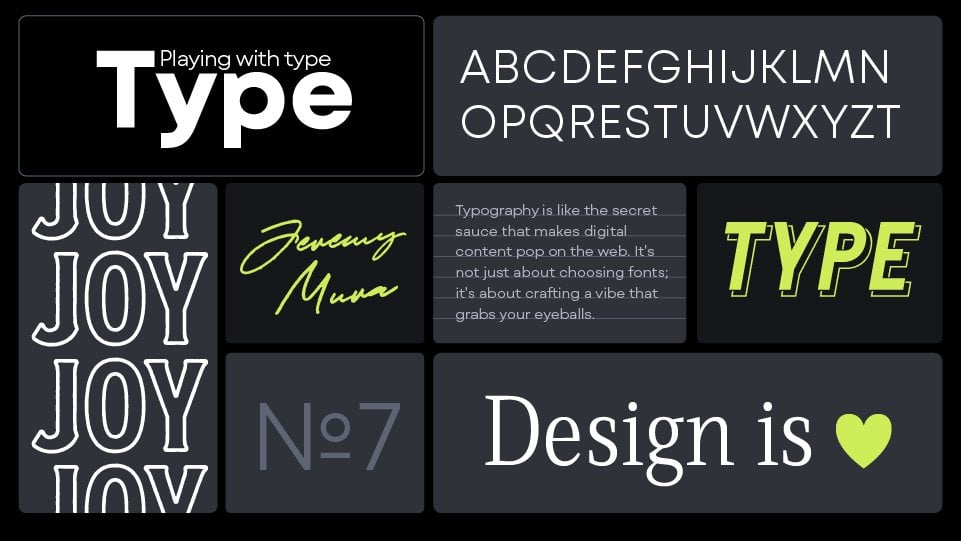
Jouer et concevoir avec la typographie pour les marques
Introduction
Inspiration et trouver des polices
Choisir les polices
Jumelage de polices
Personnaliser des polices et des logotypes
Systèmes typographiques
La puissance des glyphes
Composition et mise en page
Mon système logiciel de polices
Les besoins en typographie
9:24
Un excellent design typographique sépare les designers amateurs des pros.
Apprendre à manier des polices et les utiliser pour obtenir les bons résultats dans n'importe quel projet de conception créative.
Nous explorerons l'interaction dynamique entre type et branding, en apprenant mes méthodes de choix des polices, de personnalisation et de utilisation dans un site Web, une marque ou un design numérique.
Apprenez ceci :
✨ Maîtriser la typographie dans Branding : sélectionner et manipuler des polices qui correspondent aux identités de la marque, créer des visuels qui communiquent efficacement.
✨ Choisir et jumelage des polices : mon processus de sélection des bonnes polices pour un projet
✨ Glyphes et systèmes de polices : appliquer les principes de design et comment utiliser la typographie de manière créative
✨ Personnaliser les logotypes Développer des compétences en création de compositions typographiques visuellement époustouflantes à l'aide d'outils et de méthodes de conception numérique avancés.
✨ Exemples de clients : je vais montrer comment j'ai personnalisé des polices pour de vrais clients.
✨ Codes de triche de Jeremy : apprendre mes codes de triche pour travailler plus rapidement.
1. Introduction: Bonjour, bienvenue dans ce court cours sur la façon de jouer avec la typographie dans le domaine de l'image de marque et du design. Je m'appelle Jeremy. Je suis un designer de marque originaire de Sydney, en Australie, et je crée depuis dix ans maintenant. Et j'ai travaillé avec des clients de différentes marques. Et je crois que la topographie est à la base d'un design de qualité. Dans ce cours, vous apprendrez notamment comment utiliser la typographie dans un système d'identité Je vais donc vous montrer quelques exemples concrets de clients illustrant la façon dont j'ai sélectionné certaines polices et comment je les ai présentées pour créer une identité de marque. Je partagerai également avec vous mes conseils et réflexions sur la façon dont j'associe les polices pour différents projets. Ce qu'il faut sélectionner, comment s'y prendre, vous savez, utiliser les bonnes polices dans les bonnes situations. Je vais également expliquer comment personnaliser et choisir la bonne police et comment la manipuler dans Adobe Illustrator. Je vais également vous parler du pouvoir des glyphes et de la façon de personnaliser certaines polices et lettres lorsque vous travaillez sur la conception d'un logo Et comment faire en sorte que cela se démarque et devienne plus emblématique. Je vous montrerai également mes codes de triche, mes astuces, mes raccourcis et tous ces petits avantages en cours de route pour vous aider en tant que designer à grandir et à améliorer votre maîtrise de la Je vais également vous donner quelques devoirs et activités vous permettant de pratiquer la conception dans la section projet, afin que vous puissiez le faire pour pratiquer la conception et télécharger votre projet. Et je serais heureuse de vous faire mes commentaires afin que vous puissiez améliorer vos compétences. Alors, cliquez et lancez dès aujourd'hui et améliorez votre conception grâce à la typographie 2. Inspiration et trouver des polices: Au cours de l'année, j'ai probablement accumulé plus de 10 000 fonds. Et c'est parce que je télécharge toujours de nouvelles polices. Et chaque projet a besoin de quelque chose de différent. Et il y a toujours de nouvelles limites qui apparaissent, où il y a tout un tas de fonds gratuits très haute qualité Je veux vous montrer quelques sites qui vous inspireront, où vous pourrez télécharger des polices gratuites et acheter des fonds. Mais si vous voulez plus de ressources, je mettrai un lien dans la section du projet pour partager ma méga liste de ressources de conception. La première étape serait le partage de polices. Maintenant, ils ont 100 polices gratuites et gratuites. J'adore utiliser le partage de polices car il est puissant et propose de nombreux styles différents, quelques polices de script. Mais je l'adore parce que vous pouvez vraiment regarder différentes paires. En haut, vous avez des paires sur lesquelles je peux cliquer, cela me montrera en fait des paires différentes. La police est géniale. Un autre est le tissu de police. J'ai également utilisé leurs polices de caractères. Ceux-ci sont de très haute qualité. Ils ont des tas de styles différents. Par exemple, si je clique sur Mont, vous pouvez voir qu'il devient fin très clair jusqu' à devenir épais et noir. sites en italique comme celui-ci sont vraiment bons Pangram, Pangram propose des kits de démarrage 29$ où vous pouvez vous procurer tout un tas de polices à essayer, puis si vous en aimez certaines, vous pouvez les Ces polices sont vraiment cool, certaines sont futuristes, donc il y a plein de trucs sympas ici Vous avez également de futures polices, Xyz, elles sont vraiment géniales Il y en a une grande variété ici. Ce ne sont pas seulement des polices simples, mais aussi des polices d'affichage, rétro funky et intéressantes. Vérifie ça. Vous pouvez également vous rendre sur Creative Market. Create Market fournit également des polices de caractères. Si vous cliquez sur la section des polices, ils ont des lettres noires vintage, des graffitis cursifs fantaisistes Ils ont des tas de polices différentes. Vous pouvez également taper dans la barre. Tu peux voir à quoi ça ressemble. C'est également un excellent moyen de trouver des polices très rapidement. est un autre site sympa Nick.com est un autre site sympa. Brandon possède un studio de design typographique Il crée de nombreuses polices de caractères ici. Et il propose également ces packs, qui sont vraiment sympas, où vous pouvez trouver environ 2030 polices dedans J'adore son style. Il y a vraiment quelque chose de différent là-dedans. Si jamais vous travaillez sur des trucs rétro vintage, ceux-ci seraient parfaits pour ce type de projet. Il existe de nombreuses autres polices, comme les polices et les polices futures, etc., mais j'ai tendance à éviter les sites de polices gratuites très populaires car ils sont de très mauvaise qualité, en particulier en ce qui concerne les polices de caractères. Lorsque vous téléchargez une police, elle est défectueuse, il n'y a qu'une seule police, il n'y a pas plusieurs polices. Il ne s'agit donc pas d'une police de caractères de toute une famille de polices C'est pourquoi j'essaie d'éviter ces sites et je vais essayer de m'en tenir à ceux où j'en achète ou en télécharge un site gratuit sur un site comme Font Share, qui est tellement meilleur parce que la qualité est au rendez-vous. Vous pouvez voir qu'il a été méticuleusement conçu et fabriqué. Et il est également livré avec des glyphes et des symboles, ainsi que des variations sur différentes lettres C'est pourquoi je préfère cela, et j' essaie d'éviter des choses comme une police de caractères. Et si je tombe sur un site Web ? L'un des outils que j'aime utiliser s'appelle en fait font Ninja. Vous pouvez également utiliser quelque chose comme quelle police. Il s'agit d'une extension Chrome gratuite. Ce que je peux faire, c'est aller sur un site Web et peut-être que j'aime cette police ici. Tout ce que j'ai à faire c'est de cliquer sur la police Inga. Nous allons essentiellement scanner le site Web et me dire quelle police ils utilisent. À l'heure actuelle, je peux le voir avec Satoshi. Maintenant, Satoshi est une police gratuite sur le partage de polices. C'est la police de caractères qui s'y trouve. Ensuite, je peux placer ma souris sur la police et elle m' indiquera le poids, le fil et la couleur. Nous pouvons voir que tous ces petits détails dans cette petite boîte, vous pouvez voir ceux-ci comme 20 pixels, 15 pixels en utilisant une couleur grise. C'est vraiment cool. J'adore ça. Vous pouvez également jouer avec ces petits réglages ici. Vous pouvez déplacer la police, l' agrandir pour pouvoir la prévisualiser et jouer dessus. J'aime bien ça. Vous pouvez également ajouter les polices à vos favoris. Si vous cliquez sur le signet dans la police Inger, c'est ce qu'il fera. Voici un autre exemple. Peut-être que j'aime bien cette police ici. Essayez-le à nouveau et voyez ce qu'il en résultera. Cliquez dessus et vous pouvez voir le titre de SQL Sands ainsi que le corps du texte du titre de SQL Sands Il est à la fois de taille moyenne mais juste de plus grande taille. Vous pouvez voir le corps du texte et le titre, c'est vraiment cool. Vous pouvez littéralement l'utiliser sur n'importe quel site Web. Il vous dira simplement ce que c' est et cela vous fera gagner beaucoup de temps. C'est normal de voler des polices. C'est normal d'utiliser les fonds. Certains d'entre eux, vous devrez probablement en acheter. Mais c'est pourquoi c'est toujours bon. Si vous avez un budget supplémentaire, demandez à votre client si vous pouvez acheter une police en particulier, car vous savez qu'elle sera plus unique et distincte de toutes les autres marques sur le marché. Pour moi, je n'aime pas, vous utilisez toujours Monster, At , Poppins et Helvetica, toutes les Nous utilisons les mêmes polices et je ne veux pas le faire, je veux trouver des polices différentes. C'est pourquoi je suis toujours à la recherche d'une police particulière qui correspond à l'ambiance de la marque que je recherche. 3. Choisir les polices: Maintenant, je reçois toujours des questions de la part des designers. Comment choisir les polices pour un projet de marque ou pour un logo ? Maintenant, je me fie toujours à mon intuition, mon instinct ou à mon instinct lorsque je regarde une police de caractères. C'est pourquoi je suis toujours en train de parcourir ces différentes fonderies de polices examiner la forme de la lettre, demander ce que je ressens lorsque je la regarde, vous savez lorsque j' interagis avec elle Parce qu'en fin de compte, je dois transmettre une ambiance, une sensation et une atmosphère qui bouleversent la perception de la marque auprès des clients En fin de compte, tout dépend de la personnalité de la marque et du public. Lorsque j'ai une session de découverte de marque avec mon client ou un atelier de stratégie, j'essaie d'extraire les mots clés de la marque. Alors je sais si notre marque va être amusante ? Est-ce que ça va être très technique et minimal ? Est-ce que ça va être audacieux ? Toutes ces questions entrent en jeu lorsque j'essaie de comprendre la personnalité de la marque, puis le public. Le public ressemble-t-il à des passionnés de technologie, s'agit-il peut-être de femmes ou de mères, ou peut-être de leurs pères ou de jeunes adultes qui vont à la plage ? Il y a toutes ces questions que vous voulez poser qui vous aideront vraiment à affiner votre recherche de la bonne police. Il s'agit d'avoir ces limites et ces limites. Vous pouvez ainsi canaliser votre vision et vous concentrer sur le choix de quelques polices , puis sur leur intégration dans Illustrator Et travailler et jouer avec ça, ou même avec Figma. Et si vous concevez comme un site Web, et je le dis toujours aux concepteurs, tester plusieurs polices, placer sur le canevas ou sur votre plan de travail. Tu travailles avec. Mets-le sur une image. Qu'est-ce que tu ressens ? Mélangez-le avec quelques couleurs. Voyez ce que vous ressentez dans le mouvement que vous ressentez. Lorsque vous jouez avec la police. Je souhaite partager avec vous certains types de styles de police. Il y en a, vous le savez probablement, mais il y en a une longue liste. Mais je vais vous montrer certaines de mes préférées. Nous avons des choses comme San Serap, qui sont très modernes, uniques, simples et minimalistes Vous avez un serap vraiment classique et élégant. Vous avez un séraphin en forme de dalle, avez l'impression du Far West Très audacieux, très grand. Vous avez des polices d'affichage. Les polices d'affichage ressemblent davantage à des polices décoratives. Ils peuvent avoir de la texture, ils peuvent être rugueux, ils peuvent avoir de petits motifs. Vous avez une écriture manuscrite, comme pour les signatures, comme pour un timbre-poste ou quelque chose comme ça Le scénario est très féminin. Pétillant, ludique, à espacement fixe, cela ressemble plus à de la numérisation. Pensez à des ordinateurs binaires ou à un robot intelligent. Géométrique, très propre. La calligraphie moderne ressemble essentiellement à quelqu'un qui écrit le stylo de calligraphie Très old school, style ancien. Je suis devenu grotesque et humaniste. Ils sont assez similaires. Des lettres modernes et épurées. Ce n'est pas géométrique, mais plutôt des polices simplifiées. Si vous avez également des lettres noires comme à l'époque du vieux style médiéval, pixel pixel est idéal pour l'art en huit bits. Ou peut-être que c'est un jeu comme Stared Value ou quelque chose comme ça fait de pixels Vous pouvez utiliser une telle police. Voici quelques types juste pour vous faire réfléchir au style que vous voulez adopter. Réfléchissez. Il est bon de savoir, juste au cas où, lorsque vous présentez un moodboard et que vous voudriez le montrer à votre client, c'est le type que nous allons choisir Ensuite, il va simplement affiner votre recherche lorsque vous recherchez une police. Comme je l'ai déjà dit, lorsque je choisis une police de haute qualité, je recherche toujours les familles de polices. Combien de poids possèdent-ils ? Parce que c'est important lorsque je travaille sur un projet. Parfois, je veux juste utiliser la même police, mais juste des poids différents. je n'ai pas besoin de 234 polices parce qu'il y en a trop. J'essaie toujours de me limiter à trois polices Mac, mais d'habitude j'essaie de me procurer une ou deux très bonnes polices avec de bonnes familles. Vous pouvez donc voir que le tissu Mont Blanc from Font possède une grande famille de tissus, allant du tissu fin au noir. Et c'est très gras, gras, semi-gras, et c'est en italique pour chacun d'eux Maintenant, ces polices sur le côté droit n' ont qu'une seule police. Désormais, la police est composée d'un seul style ou d'un seul poids. Ce n'est pas une famille , c'est un type de visage. Vous pouvez voir que vo n'a qu'une seule police, c'est juste normal. Et Hand Gothic n'a qu' une version normale et vous pouvez voir deux polices différentes. L'un est un séraphin en forme de plaque, alors celui-ci est plutôt une police d'affichage Et ils ont l'air cool, mais c'est très restrictif. J'utiliserais probablement ces polices, probablement uniquement pour les titres et non pour le corps du texte. s'agit de trouver des sites Web qui ont réellement des filtres différents. Vous pouvez le voir sur le partage de polices, ils ont des filtres dans la section des catégories où je peux effectuer une recherche par style, poids, largeur, contraste et bords, et hauteur x, et je peux effectuer une recherche par personnalité. Cela va donc rendre ma recherche beaucoup plus rapide lorsque je recherche des attributs spécifiques, n'est-ce pas ? Si vous en avez l'occasion, jouez avec certains de ces paramètres et cela accélérera considérablement votre recherche lorsque vous recherchez une police en particulier. Vous avez donc appris à connaître la personnalité de la marque, ce qui vous aidera à rechercher la bonne catégorie de police. Voici un exemple rapide. J'ai quelques mots clés sur la gauche que j'ai l'habitude d'utiliser pour un projet de marque très différent. Et c'est la police que j'ai choisie sur la droite. Donc, tout d'abord, nous avons le moderne, le minimal et le propre. Et je pense au code, je pense au code. Ensuite, c'est très géométrique, c'est une police propre. C'est sympa, c'est très lisible et lisible, facile à lire. Le suivant est vintage rough et masculin. Quand je pense à ces mots clés, je pense à SS. Nixon. Très audacieux, très découpé. C'est un peu rugueux sur les bords. Il y a cette touche masculine à cause de son audace Les lettres sont uniques. ressemble un peu au plein air, à l' aventure, au camping, Cela ressemble un peu au plein air, à l' aventure, au camping, à une touche de style, mais aussi à un peu de vintage, comme sur une bouteille de whisky ou quelque chose comme ça Enfin, nous sommes élégants, classiques et raffinés. Je pense à quelque chose comme Baskerville. Ce n'est qu'un bref exemple de ce que je choisirais. Cela ne signifie pas que je ne choisirai que ces polices pour le projet, cela vous donne juste une idée de quelque chose. Je vais sélectionner quelque chose de très similaire à ces styles de polices. C'est pourquoi je dis toujours aux gens, que vous soyez Figma ou Illustrator, quelle que soit l'application que vous utilisez, toujours définir un texte, de mettre en place un ensemble de polices, le restreindre et de sélectionner vos préférées, comme les trois ou les cinq meilleures Ensuite, commencez à jouer avec eux et à voir lequel correspond à la personnalité de la marque et aux mots clés de la marque. Je veux montrer un exemple rapide de. J'utilise juste le casque VR de Meta. C'est le Metaquest Three, la police que nous utilisons ici est le code suivant Vous pouvez donc voir que c'est très moderne , propre , futuriste et solide. Mais maintenant, si nous passons à la diapositive suivante, nous allons utiliser la police Nixon. Cela ne semble pas à sa place. L'utilisation de la bonne police est vraiment importante. J'utilise, je crois, c'est Nixon, six ou sept pour le bas et les autres polices. C'est un peu trop rigide, j'ai l' impression d'aimer l'ambiance spatiale, même un peu gamy et les autres polices. C'est un peu trop rigide, j'ai l' impression d'aimer l'ambiance spatiale, même un peu gamy Là où nous ne cherchons pas ce look de jeu, nous optons pour un produit haut de gamme. Et puis vous pouvez voir sur la gauche que la police est Baskerville C'est une police élégante comme celle-ci qui pourrait fonctionner. Mais vous pouvez voir qu'une fois qu' on regarde le corps, il semble un peu démodé, un peu déplacé. Vous pouvez consulter les prix ici. Et en bas , je ne sais pas, il semble un peu faible, alors que le premier fonctionne. 4. Jumelage de polices: Maintenant, comment associer des polices ? J'ai l'impression que beaucoup de designers y réfléchissent trop et pensent qu'ils doivent être parfaits lors du choix de la police Mais le principe de base auquel je pense lorsque j'associe des polices est le contraste Il s'agit d'établir des contrastes entre les titres, le corps du texte et d'avoir cette hiérarchie avec les différents types d'informations que vous utilisez. Par exemple, voici un design rapide que j'ai créé. J'ai trois exemples ici. Deux sur la gauche ne sont pas les meilleurs. Je vais vous expliquer pourquoi, car il y a un manque de contraste. Maintenant, vous pouvez voir que le titre de ce premier titre est très fin. Le titre doit être en gras. Il doit être facile à regarder très rapidement lorsqu' personne arrive sur un site Web ou sur une page qu'elle est en train de lire. La police ci-dessous est la même que celle-ci. Comme vous pouvez le voir, j'utilise tous les deux Mont Blanc pour cette lumière et cette lumière, elles sont toutes les deux de couleur blanche. C'est gênant pour les yeux lorsque couleurs se contredisent et que c'est trop clair, cela les empêche de lire le corps les couleurs se contredisent et que c'est trop clair, cela les empêche de lire le corps du texte. Celui-ci ne fonctionne pas. La seconde, vous pouvez voir que celle-ci est très audacieuse. Mais cela a alors une très large avance. Il y a beaucoup d'espace entre les lignes et j' ai juste l'impression que cela traîne dans les yeux, faut rebondir beaucoup plus loin et beaucoup plus Cela cause de la fatigue lorsque vous le lisez. L'audace du titre fonctionne. Mais alors c'est mauvais. Vous pouvez également voir ce chiffon. Maintenant, le chiffon est essentiellement la forme créée par le texte du paragraphe, c'est pourquoi j'ai mis une ligne ici Ces deux-là ont un très mauvais chiffon. C'est l'exemple qui s'y trouve. Mais voici le dernier exemple que j'ai fait. Vous pouvez voir que j'utilise Montblanc semi-gras, puis Montblanc normal Pour cela, j' ai réduit la couleur à une couleur grise. Comme vous pouvez le voir ici, j' utilise ce code hexadécimal ici. Alors celui du haut est tout simplement blanc. J'ai créé un contraste avec la couleur du corps et de l'en-tête. J'ai également rendu la tête plus audacieuse que le corps, et j'ai également ajusté le relâchement, pour qu'elle soit un peu plus serrée, donc vous pouvez voir qu'elle est un peu plus serrée que l'autre C'est agréable à regarder et à lire. Même s'il est plus faible en Ipsm, il est plus agréable au toucher, plus propre et lisible Voici quelques exemples de types de polices que vous pouvez potentiellement associer. Ce n'est pas limité à cela, mais j'essaie juste de vous donner quelques idées. Une solution simple serait comme un séraphin de sable. Avec le serafont, mais avec le séraphin, mettez-le probablement en minuscules et le titre peut être en majuscules. D' habitude, j'aime bien faire ces majuscules habitude, j'aime bien Et puis peut-être un corps de serf, un titre que vous pouvez faire comme du grotesque et Ce serait une forme d'entreprise plus futuriste et plus moderne Et puis un script avec un simple séraphin. Ce ne serait pas audacieux. Ce serait probablement léger ou normal et ce serait une minuscule ou quelque chose comme ça. Voici quelques appariements potentiels que vous pouvez avoir. Les limites sont infinies. En gros, tout dépend la marque et de l' idée créative que vous recherchez. Maintenant, je veux que vous vous en souveniez lorsqu'il s'agit d' atterrir sur un site Web ou de concevoir quelque chose. Les titres numériques sont destinés à être scannés. Les gens ne lisent pas le scan lorsqu'ils sont sur une page Lorsqu'ils lisent un carrousel, lorsqu'ils arrivent sur un site Web, leurs yeux se déplacent de gauche à droite en forme de pliage en Z. Ils scannent simplement en regardant les gros titres. De plus, lorsque certaines personnes lisent des rapports de journal, elles ne lisent pas tous les petits textes. Ils regardent d'abord les gros titres. Si c'est intéressant, ils commenceront à lire le corps du texte. Et le corps du texte doit toujours être lisible ou lisible Maintenant, quand je pense à la lisibilité, je me demande à quel point c'est facile à comprendre, à lire et à quel point mon cerveau peut comprendre les lettres et les mots Passons maintenant rapidement à quelques exemples qui me plaisent. Celui-ci, c'est Bowery.com. C'est comme une entreprise de restauration. Ils expédient essentiellement des aliments et ils ont des recettes et des trucs comme ça. Et j'adore l' audace de cette police. Tout est en majuscules, c'est sympa. Mais ils ont une police simple ici, et je vais utiliser fontina pour vous la montrer rapidement Ils utilisent GT America puis National pour compresser. Vous pouvez voir ce joli petit corps, il est facile de lire. Alors vous avez GT Mono ici. Mais vous avez aussi ce grand national audacieux, qui se démarque tout simplement. C'est bon. Il essaie de plaire à un public plus jeune. Revenons à l'idée de contraste. Vous pouvez voir que nous avons un titre en gras, puis un titre lisible à la lumière, entouré de nombreux espaces blancs Vous pouvez voir que la location n'est pas si serrée, ce qui est une bonne chose. Il y a de la place ici, celui-ci. Vous pouvez voir la location ici. Ils font beaucoup de location parce que cela va interagir avec cela. Ils ne voulaient pas que le G touche ça. Je le comprends parfaitement. J'adore façon dont ils ont utilisé les majuscules ici, mais ici, ils n' utilisent pas toutes les majuscules. Parce que lorsqu'il s'agit de mots en majuscules, vous ne voulez que des mots courts. C'est vraiment difficile à lire quand les phrases sont longues. C'est pourquoi il est facile de lire les minuscules, car notre cerveau peut comprendre et comprendre la forme des mots et des lettres C'est ainsi que notre cerveau traite les choses. Mais oui, voici un bref exemple de son utilisation, qui met contraste les super-héros lourds et légers C'est comme le site d'une agence. Ils ont opté pour une grande police sans gras pour les gros titres. Et puis ils ont aussi ce ninja de Serafont. Ils utilisent l'affichage gular, le noir et le circulaire, gras standard, le P Editorial ultra léger La raison pour laquelle je pense qu'ils ont choisi ce Serafontce. Il s'agit d'un séraphont condensé. Alors ce gros titre est très large. C'est pourquoi ils ont opté pour un format condensé et un format large. Si je fais défiler l'écran vers le bas, vous pouvez voir qu'ils voulaient que leur texte soit vraiment gros. fait d'avoir un séraphin condensé lui permet de s'intégrer parfaitement dans cette forme rectangulaire Dans cette mise en page. Ce verrou est là, comme on peut le voir. C'est léger, le gras se démarque, facile à lire, vous êtes condensé, vous êtes large. Vous pouvez donc voir cette police. Comme je l'ai dit, il est large et audacieux. Et puis, si ce n'était pas condensé, cela irait jusqu'au bout, comme si c'était probablement le cas ici. Mais comme il est condensé, il se trouve ici et dans ce joli petit enclos. Maintenant, si vous avez du mal à associer certaines polices, voici trois sites que je vous recommande de consulter. Sur typeof.com, ils ont des listes de contrôle et des ressources incroyables, mais ils ont un lookbook de jumelage de caractères que vous pouvez acheter, ce n'est pas gratuit, mais il est parti de l'avant et vous a créé quelques polices de caractères . C'est déjà fait pour toi, c'est environ 40 dollars. Mais vous pouvez voir qu'il existe des versions différentes. Le luxe rétro réchauffe la technologie. Si tu aimes faire ça, c'est une idée. Vous avez également tapé inspiration.com, ils ont déjà combiné différentes polices Et je trouve ça vraiment cool, il y en a quelques-unes ici. Il n'en a pas des milliers, mais il contient juste quelques exemples de ce que vous pourriez utiliser. Je pense que c'est vraiment sympa. Je peux cliquer dessus et ensuite je peux voir quelle est la police. Vous pouvez l'obtenir sur Google Fonts, qui est gratuit. J'aime bien la façon dont ils l'ont disposé ici, juste avec quelques grumeaux dedans Enfin, nous avons Font share. Ils ont un menu à deux. Si vous allez en haut, vous pouvez cliquer sur Pairs, puis vous pouvez descendre et il y a tout un tas de paires utilisant leurs propres polices intégrées qu' ils ont déjà conçues Vous pouvez ajouter les styles, vous pouvez les ajouter. Vous pouvez modifier le texte à la volée et peu importe. Peut-être avez-vous un exemple de copie que vous souhaitez utiliser pour votre client. Vous pouvez simplement le mettre dedans et avoir une idée plus rapide de ce à quoi il ressemblera. J'adore, je vous indique les polices s' y trouvent, je peux cliquer dessus pour y accéder. Voici quelques ressources que je vous recommande d'utiliser. 5. Personnaliser des polices et des logotypes: Lorsque j'ai trouvé une bonne police que je vais utiliser pour un projet, elle correspond à la personnalité, alors j'adore la personnaliser un peu. Il n'est pas toujours nécessaire d'ajouter beaucoup de détails à un type de logo ou à un design de logo. D'habitude, c'est mieux quand c'est simple et qu'on réduit les détails, mais j'aime bien ajouter des symboles, des petits motifs ou des idées sur certaines lettres. Ou pour ajouter quelques idées et ajouter de la saveur, rendez-le plus distinct. Voici quatre logos conçus pour les clients, à l'exception de Sylfon qui était destiné à un projet parallèle Ce sont les polices que je choisis. Sur le côté gauche, vous pouvez voir celui-ci est non, c'est la tenue de celui-ci. Celui-ci, c'est Nesta. Et puis Calisto Voici à quoi ressemble la police, une police par défaut. Noah, tenue moyenne, taille moyenne, nist géométrique noir. Et voici Calisto Bold. Voilà à quoi ça ressemble sans rien ajouté. Alors voici à quoi cela ressemble lorsque j'ai ajouté quelques petits détails. service aux personnes handicapées d'Angel Hearts Healthcare et d'autres services de santé existent à Sydney. Vous pouvez voir que j'ai ajouté une petite forme de cœur d'amour à l'intérieur de cette barre transversale dans le A, ce qui est sympa. Il peut également ressembler à un livre ou à un oiseau. Le crénage a été ajusté, par exemple, vous pouvez voir ici le R et le T. Il y a eu quelques problèmes Il suffit de le serrer et de resserrer le H, réunir les mots pour qu'ils soient espacés. Et puis ajoutez-y une petite sous-ligne. Comme vous pouvez le constater. Ça s'est avéré vraiment sympa. Tout ce que j'ai fait, c'est tout mettre en majuscules , puis je l'ai bien aligné pour que vous puissiez voir que tout est aligné. Ensuite, ce que j'ai fait, c'est y ajouter un château fort parce que cette marque installe des portes de sécurité dans les maisons Tout est une question de sécurité. J'ai pensé à Castle car je voulais ajouter quelque chose d'un peu subtil. C'est parce que j'avais une version où j'avais comme un cadenas ici, comme un cadenas, puis je faisais en sorte que tout cela soit colorié ou quoi que ce soit d'autre. C'est une idée que j'ai eue, mais j'ai décidé qu'elle ajoutait trop de détails. J'ai reculé, j'ai fait en sorte que les choses soient simples. Et vous pouvez voir cette petite touche de légendes de Mobile Tire. Voici à quoi cela ressemblait avec la police. La police est très audacieuse et condensée. Lorsqu'il s'agit d'aimer de longs mots ou de longs noms de marque, il est préférable d'empiler les polices. C'est ce que j'ai appris, parce que c'est simplement plus facile à lire. C'est facile. De plus, ce qui concerne l'évolutivité et la lisibilité sur les petites tailles et les sites Web, etc., il vaut mieux empiler C'est pourquoi je les ai empilés comme ça et j'ai ajouté leur petit logan ou leur petit éclairage sur le côté Ce que j'ai fait, c'est tout resserrer pour qu'il soit compact. Ensuite, j'ai ajouté cette flèche en haut de la barre T. Je l'ai fait parce que je voulais y ajouter du mouvement dynamique. Je voulais également montrer qu'une flèche peut représenter le fait d'avancer, aider quelqu'un à conduire sa voiture pour qu'il puisse avancer et se rendre au travail ou rentrer chez lui en voiture. Parce que si vous avez un pneu crevé, vous êtes coincé. Hein ? Vous pouvez voir certaines des idées auxquelles je pensais lorsque je l'ai fait. Et puis j'ai ajouté cette petite découpe ici pour que la flèche ressorte un peu plus. Vous pouvez voir sans cette petite coupure, comme si tout allait bien, mais vous avez juste l'impression qu'il n'y a pas assez d'espace blanc. Je l'ai juste retiré pour le faire respirer un peu. Pour le rendre un peu plus avant-gardiste, j'ai aligné la flèche sur le bord Comme vous pouvez le voir, il est aligné, ce qui ajoute quelque chose de bien. J'aurais pu l'amener jusqu'au bout comme ça, mais ça commence à me distraire un peu trop Je vais donc le ramener au R. J'aurais aussi pu faire ceci ou comme ça, cela pourrait aussi fonctionner. Vous pouvez toujours voir que c'était une légende de l'époque pour le petit G, j'en ai fait un éclair, ce qui était amusant, le client l'a aimé. C'était quelque chose de différent, j'en avais marre du mobile. Je pense aux légendes juridiques, le gars était aussi un joueur Je suis du genre, oh, mettons juste un éclair. C'est différent, unique. Enfin, Sylpi ici, nous pouvons voir à quoi cela ressemble, la valeur par défaut Ensuite, l'ajout de ces petites découpes lui donne un aspect beaucoup plus différent, futuriste. Vous pouvez voir que j'ai ajouté ces petites coupures ici, puis que je les ai arrondies. Sur celui-ci, j'ai ajouté cette petite forme ici. Si je retirais ce qui n'était pas là à l'origine, c'était comme si un espace blanc normal alignait bien le tout. Et vous pouvez voir qu' un petit slogan ajouté s'intègre parfaitement à cette forme. Vous pouvez voir qu'il tient bien dans cette petite boîte ici. Dessiner n'est pas ce que l' on voit de mieux . Il y a comme un rectangle. Il est aligné en bas. Tu comprends, mais ça fait du bien. Fturisticjtdding de petites coupures puis ajout de cette étiquette. Comment j'ai fait en sorte que ces logos soient distincts et qu'ils aient l'air différents, par rapport au simple fait d'ajouter la police et d'arrêter. Et dire : « Hé, c'est du design ». Je veux essayer d'ajouter un peu plus de détails, plus de qualité. Ajoutez cette touche de design de logo, cette touche de designer. C'est pourquoi je l'ai fait. Voici maintenant quelques exemples supplémentaires de personnalisation des polices Pas dans le sens du logo, mais simplement dans le sens générique. Ce que j'aime faire, c'est voici quelques façons dont j'aime le faire. La première est que rien n'est ajouté au texte. Il s'agit simplement d'un bloc de texte normal. Une chose que vous pouvez faire est d'ajouter de la couleur. Vous pouvez voir ajouter un bleu et un rouge ici. La couleur fonctionne. Vous pouvez également ajouter une échelle. Dans celui-ci, j'ai réduit la première partie de la phrase , et celui-ci en gras. La raison pour laquelle je fais cela est que je veux mettre l' accent sur le mot créativité, n'est-ce pas ? Il peut être utilisé comme support marketing, peut-être pour une université ou quoi que ce soit d'autre. Je tiens simplement à le souligner. Vous pouvez également créer un effet de haute lumière en ajoutant un marqueur en surlignant des objets ou les utilisant comme un marqueur et dessinant un peu comme des flèches emojis ou autre, ou des icônes Vous pouvez utiliser des couches épaisses et fines. Revenons à l'idée globale du contraste. Un texte peut simplement être très clair et l' autre en gras. Cela fait ressortir ces mots parce que je veux attirer l'attention sur ces mots. Nous pouvons utiliser l'italique, pour que cela fonctionne également. Cela peut être très subtil. Vous pouvez taper des majuscules, peut-être en majuscules, puis l' autre en minuscules. C'est une autre façon de le rendre différent. Tu peux faire de l'opacité. Celui-ci, je baisse l'opacité à 30 %, il paraît gris Évidemment, j'aurais pu changer la couleur gris si j'avais joué quelque chose derrière cela Vous pouvez voir qu'à cause de l'opacité, cela va s' infiltrer et Mais si vous ne voulez pas que cela se produise, remplacez-le simplement par une pointe rapide grise. Enfin, vous pouvez réellement masquer des choses. J'ai masqué une image dans le jardin que je peux déplacer C'est aussi une façon amusante personnaliser une police, rendre différente, de la rendre intéressante. Lorsque j'utilise certaines de ces techniques, j'essaie d'éviter de toutes les additionner. Je pourrais juste en faire une ou deux. Je ne vais pas ajouter de masquage , puis aussi beaucoup de couleur et d'italique C'est tout simplement trop. Ça va vous distraire, à moins que ce ne soit une marque vraiment amusante Vous pouvez peut-être en mélanger quelques-uns, mais essayez d'en choisir un ou deux. Il suffit d'un style ou d'une seule chose pour souligner un mot. Enfin, je joue et je fais en sorte que cette petite maquette rapide en Y en ligne utilise l'IA et j'ai créé cette image. Ensuite, j'utilise la police en pixels que je n'utilise pas normalement. Vous pouvez voir que j'ai juste ajouté une petite ombre et que j'ai ajouté du texte rouge pour le personnaliser. Je l'ai mis dans un coin ici parce que ça donne l'impression qu'il y a quelque chose de plus en bas. Je peux faire défiler la page vers le bas et peut-être même ajouter une petite flèche ou quelque chose comme ça. Ensuite, vous pouvez ajouter la police ici et à quoi pourrait ressembler le site Web. J'ai juste joué avec la police, et c'est un bon moyen de tester les choses. Si j'ai juste besoin de changer des choses, je peux littéralement tout sélectionner. Et puis, ce que je peux faire, c'est changer la police d'écriture. Peut-être que je veux en choisir un autre. Peut-être que je veux intervenir et opter pour une plus grande légèreté ou pour faire preuve d'audace. Je peux essayer ça et voir qu'il y a une ambiance différente, non ? Mais avec la police en pixels, c'est tout simplement différent. Mais il est facile de changer de police, que ce soit dans Figma. 6. Systèmes typographiques: Si vous voulez concevoir un système typographique pour une identité de marque, c'est essentiellement comme avoir un système, ou un guide de style, ou un système de conception pour un site Web d'interface utilisateur ou autre C'est la même chose. Il s' agit simplement d'avoir des styles définis. Définissez des tailles pour les titres, le corps du texte, les boutons, les étiquettes, les liens d' une marque et d'un site Web. C'est vraiment tout ce que c'est. Quand je pense à la création d'une sorte de système, je pense toujours à n'importe quel type de balises H one H 2h3h4 parce que c'est ainsi que Hmil est lu lorsque je conçois flux Web ou n'importe quel framer, quelle que soit Vous devez réfléchir à la manière dont les sites Web sont créés en HTML et en CSS Je pense à chaque balise de titre, à chaque paragraphe, je pense aussi aux liens, aux boutons, à la hauteur des lignes, au crénage, à la pondération des caractères, toutes les fonctionnalités clés de l' apparence d'une police ou d'un texte dans un certain espace Par exemple, mon propre site Web personnel, c'est mon système que j'ai utilisé. Pour mon H one, mon titre principal, il fait 64 pixels. Et vous pouvez voir que j'utilise la police sine et le semi-gras. Le H deux fait 25 pixels, j'utilise le sinus et le gras. Et puis vous avez le H trois, le H quatre, et ils ont tous un aspect très différent. Et c'est parce que je veux que mes titres et mes textes soient variés. Ensuite, vous avez le corps du texte, grand, moyen et petit. Vous pouvez y voir la taille, 22 pixels, 18,16, puis un bouton Ce bouton ressemble à celui de mon site Web, 16 pixels. Ensuite, il y a évidemment d' autres boutons et d'autres petites portions de texte. Le potier a également un microtexte. C'est un peu plus que cela, mais c'est le texte principal général dont je dispose lorsqu'il s'agit de créer un système typographique Cela peut être très large, mais lorsqu'il s'agit d'un simple site Web ou d'une marque, cela ne doit pas être si compliqué. Tant que vous comprenez les principaux titres, le corps du texte, puis les liens, les boutons et tout le reste, tout devrait bien se passer. excellent site Web que j'utilise pour déterminer le type de balance que je vais utiliser est le type Scale.com. Il me donne un système ou un modèle de différentes tailles Vous pouvez passer en deuxième position, vous pouvez cliquer sur la touche majeure en troisième position. Je vais juste vous donner quelques ratios différents, essentiellement que vous pouvez utiliser lorsque vous créez un site Web et même si vous voulez créer une marque. Mais c'est particulièrement utile lorsque vous devez avoir un site Web. Et vous pouvez le voir ici, cela va changer son apparence, ce qui est cool. En gros, ça me donne le HM, puis ça me donne le Rem. Vous pouvez également cliquer sur les pixels si vous le souhaitez. Si vous voulez regarder en pixels, j'utilise généralement M lorsque je crée un flux Web C'est simplement mieux parce que l'échelle du texte est meilleure. Il est plus réactif et est connecté au HTML inhérent. Au lieu de simplement lui donner un pixel défini, j'utilise ce calculateur. C'est Necococ.com où je peux changer les pixels , puis je vais me donner le M. J'ai mis le M dans la section topographie de Webflow, mais ça va être Ouais. Vous pouvez choisir des échelles. D'habitude, j'utilise juste le major 30, c'est ce que j'utilise habituellement. Mais tu peux faire ce que tu veux, tu peux enfreindre les règles. Certains sites ont un texte incroyablement gros et c'est le design qu'ils ont choisi. Cela dépend vraiment de vous, mais tiers majeur ou -30 est généralement le plus courant. Et vous pouvez voir le style de votre paragraphe, texte, de votre petit texte, etc. Un seul conseil. Lorsque vous concevez pour un site Web, je m'assure que la topographie ne descend pas dessous de 16 pixels, sauf si elle est très micro Et ce n'est pas un appel à l'action. C'est juste là parce que si vous descendez en dessous de 16 pixels, cela devient illisible Nous parlons toujours d' accessibilité. Facilitez la tâche des personnes susceptibles d'avoir un handicap en évitant de trop réduire le texte. Mais tu peux probablement aller aussi loin que tu le souhaites. Tu peux l'agrandir. Vous pouvez augmenter la taille du titre. Je peux cliquer sur le signe plus ici. Oui, cet outil cool. Je peux changer la police. Je veux utiliser une épaisseur de police différente. Tu as aussi la hauteur de la ligne. Vous pouvez modifier l'espacement des lettres. Je peux changer de couleur si je le souhaite. Vous avez vraiment le contrôle de ce à quoi cela peut ressembler. Ensuite, vous pouvez simplement copier ceci et vous pouvez le coller, par exemple, je peux le coller, je peux coller la taille, et vous pouvez voir qu'il va atteindre la taille que je viens de sélectionner ici, 61 pixels. Voici maintenant quelques exemples que vous pouvez utiliser pour voir d'autres marques dotées d' un système typographique Et je les aime bien parce que c'est très simple. Nous avons du courrier, vous pouvez voir us.mailchimp.com Il s'agit de leur bibliothèque ou leur guide de style pour la typographie Vous avez leur police principale, elle s'appelle Means, ce qui est cool, puis Graphic est leur police de support Nous pouvons voir l'échelle ici : vous pouvez voir titre 123, le corps du texte en gras, puis les boutons et les étiquettes ou tout autre paragraphe puis un exemple de la façon dont il est utilisé Il est bon de montrer un exemple, surtout si vous créez un graphe de style pour votre client. Ensuite, voici les classes, c'est le CSS, façon dont il est stylisé, qui est destiné au Web Lorsqu'il s'agit de créer du texte. J'utilisais beaucoup Laura ipsum par le passé, mais l'une des solutions est que vous pouvez utiliser Gloom ipsum si vous ne connaissez pas Realoum s'agit en fait d'une application basée sur l'IA que vous pouvez Cela génère quatre années vraiment géniales. Mais ils ont un plugin Figma génère du texte pour vos pages de destination C'est mieux que de vous en faire une copie vous-même. Personnellement, j'aime utiliser Chat GPT pour générer du texte au lieu d'avoir Lauren ipsum Chaque fois que j'ai un projet client ou un projet parallèle, je peux générer des titres de texte, etc., car c'est plus réaliste et vous pouvez mieux visualiser la marque avec le texte que vous avez créé au lieu de simplement mettre Lauren Ifs. Ça montre juste que tu es un peu paresseux. De plus, à moins que ce ne soit comme votre MVP, vous essayez juste de trouver quelque chose, c'est bon Mais une fois que vous avez commencé à vous lancer dans les révisions et les itérations de la conception, vous devez commencer à utiliser le texte approprié Je vais simplement vous montrer un système de typographie simple que j'ai créé pour cette marque sur laquelle je travaille. Et c'est assez simple. Rien de trop complexe. C'est juste pour une petite entreprise. En général, je donne un exemple de ce à quoi ressemblerait le texte. J'ai montré le nom, puis quoi ressemblerait le titre, les sous-titres, les paragraphes, l' exemple de la façon dont il pourrait être Pour cet exemple, j' utilise la police puis ou le semi-gras pour les titres. Ensuite, passez régulièrement aux textes des paragraphes, aux liens et à d'autres choses de ce genre. En voici également un exemple en majuscules. Parce qu'à ce stade, c'était comme au deuxième round et je ne savais pas si je voulais opter pour les majuscules ou les minuscules. Cela peut fonctionner dans les deux cas, mais je voulais juste montrer quelques exemples pour voir à quoi cela ressemble pour le client Et puis ce que je fais, évidemment, je le mets sur des maquettes, comme vous pouvez le voir ici, comme vous pouvez le voir, comme une maquette de voiture, qui est un t-shirt cool. Ensuite, ce à quoi cela ressemblait sur la page de destination, c'était juste au premier tour de la page de destination. Très vite, vous pouvez voir comment j'ai disposé le texte dans les boutons, le titre, le texte du paragraphe Vous pouvez voir ce que j'ai montré tout à l'heure. En gros, il suffit de l'exposer et de voir comment il fonctionne. C'est ainsi que vous pouvez avoir un système de type simple. S'il s'agit d'un client complexe, faut avoir comme H1h2 Dans ce cas, je mets simplement des sous-titres, des titres , des paragraphes pour le rendre plus facile à comprendre, car votre client pourrait ne pas comprendre comme les termes de développement ou le jargon Vous voulez donc que les choses restent simples. 7. La puissance des glyphes: L'avantage d'Adobe Illustrator, c'est que vous avez le pouvoir de personnaliser les glyphes Maintenant, les glyphes sont essentiellement des symboles et d'autres éléments tels que des ligatures ou différents nombres non doublés, des choses comme ça Lorsqu'il s'agit d'une police, les polices de meilleure qualité contiennent généralement beaucoup de glyphes Il suffit de taper, puis de cliquer sur les glyphes J'ai le mien ici, sur le côté gauche. Vous pouvez voir que si je clique sur cette police, tous ces glyphes s'afficheront Je vais le mettre ici. Vous pouvez voir tous ces différents symboles. Je peux l'agrandir en appuyant sur la montagne en bas à droite, pour l'agrandir. Je peux modifier le poids de la police et les glyphes changeront en fonction de ce poids Revenez à la normale pour le moment. Vous pouvez également modifier la police. Peut-être que je veux me tourner vers Montreal Jazz ou Different one into V. Comme vous pouvez le voir, il y en a beaucoup de différents. Vous pouvez également cliquer sur Afficher pour n'afficher que certaines parties. Peut-être voulons-nous montrer, peut-être que les figures de doublure me montreront juste les chiffres ou les ligatures Et nous avons quelques ligatures ici, il y a vraiment un contrôle total Certaines personnes que je vois essaient de créer un T comme un symbole de copyright, mais vous pouvez simplement double-cliquer et l'ajouter. Je voudrais montrer un exemple. Je veux que tu devines combien de glyphes il y a ici. Je ne sais pas si vous avez bien saisi le chiffre, mais il y a en fait six glyphes dans ce dessin, qui est assez inattendu Mais je veux vous montrer ce que j'ai fait ici. Tout d'abord, nous avons le symbole de marque TM. Je vais juste récupérer mes glyphes. Il est si facile d'ajouter des glyphes. Tout ce que vous avez à faire est de sélectionner un élément n'importe où le long de cette ligne de texte, il vous suffit de double-cliquer. Il ajoute littéralement le glyphe pour vous. Nous pouvons voir que nous pouvons double-cliquer sur autant de glyphes que nous le voulons C'est juste puissant parce que nous pouvons réellement créer de meilleurs caractères avec cela. Parce que parfois, les gens se contentent du générique. Si je fais juste les guillemets, parfois ce ne sont pas de véritables guillemets, c'est juste l'apostrophe Mar, et c' Je veux des guillemets appropriés. S'il s'agit d'une citation, la façon dont vous la modifiez en glyphes peut également entraîner pertes de glyphes, même lors de la conception Nous avons également ce glyphe ici, qui est une flèche. J'adore quand il y a des flèches et des objets avec lesquels on peut jouer. Vous pouvez voir ces flèches en bas de page. Je peux appuyer sur le clic gauche sur le double clic. Ensuite, je vais simplement l'étendre. Comme vous pouvez le constater, nous pouvons simplement jouer. Nous avons également ce numéro ici. Celui-ci est un glyphe, il y a un glyphe. Cette flèche est également un glyphe, et le reste n'est que du Maintenant, si vous voulez faire une ligature, vous devez la sélectionner, accéder aux ligatures, puis double-cliquer pour la joindre Jouez avec les glyphes si cool et si puissant et vous obtiendrez de meilleurs résultats lorsque vous concevez pour moi. J'ai l'impression que les glyphes sont résultats lorsque vous concevez pour moi. J'ai l'impression que les glyphes sont sous-estimés. Les gens ne l'utilisent pas assez. C'est idéal pour les présentations avec différentes mises en page, jouer avec les formes, les lettres, etc. Et vous obtiendrez bien d' autres designs uniques. Mais il n'est pas toujours nécessaire d'utiliser des glyphes. Cela dépend vraiment de vous. Mais vous avez le pouvoir créatif de l'utiliser également. Vous pouvez même voir que cet astérisque est également un glyphe. Assurez-vous d'utiliser des glyphes dans votre design. Je pense que c'est un excellent outil et assurez-vous d'obtenir ces polices premium, car elles contiendront plus de glyphes que les polices gratuites 8. Composition et mise en page: Un autre facteur important pour créer une typographie de qualité est la compréhension de la composition et de la mise en page Maintenant, je ne vais pas entrer dans tous les derniers détails sur la façon de créer des grilles et d'autres choses de ce genre Il existe d'autres cours. Je vais juste me concentrer sur certaines choses pour lesquelles je suis vraiment douée et que je sais créer. Par exemple, nous avons un pentagrund, ce musée d'histoire naturelle Ils ont changé de nom et vous pouvez voir comment ils utilisent le texte d'une manière semblable à un motif, comme vous pouvez le voir dans un mouvement circulaire Je pense que c'est vraiment cool. Il ajoute un mouvement dynamique. Cela rend les choses amusantes, différentes. J'adore la façon dont ils l'utilisent sur la signalisation et d' autres choses de ce genre. Si je passe à Illustrator, vous pouvez voir comment je l'ai créé. C'était assez simple. Rien de trop dingue. Faites-le petit. Maintenant, tout ce que vous allez faire pour créer cet effet, c'est d'avoir une police. J'utilise BBW ista pour cela. Tout ce que je veux faire maintenant, c'est changer de couleur. Nous avons maintenant ces trois textes. L'un des outils intéressants que vous pouvez réellement utiliser est d'aller à l'objet, répéter et de passer à la répétition radiale. Si je clique dessus, cela créera cet effet. Maintenant, ce que je peux réellement faire, c'est le réduire. Je peux faire glisser ce grand cercle blanc avec des flèches pour augmenter le montant. Comme vous pouvez le constater, si je peux augmenter, cela semble vraiment bien. Le seul problème est que le M n' est pas aussi condensé que les autres lettres, il commence à se chevaucher. Et comme j'ai sélectionné toutes les lettres ensemble, c'est ainsi que cela va fonctionner. Je peux en augmenter la taille juste pour fixer l'espacement un peu comme ça. Ensuite, je pourrai le redimensionner. Maintenant, c'est un peu plus lisible. Cela aurait besoin d'être peaufiné et tout ce genre de choses. Mais je pense que c'est un moyen simple de créer un effet similaire à celui de Dawn dans un grand studio. Évidemment, vous pouvez faire les choses manuellement dupliquer les lettres et les arrondir sur un chemin. C'est également une option. Mais ce n'est qu'un moyen rapide d' obtenir cet effet. C'est un exemple de mon ensemble de capacités. Maintenant, lorsqu'il s'agit de mises en page, il est toujours bon d'avoir de l'échelle Vous voulez que les informations clés, le texte principal ou les principaux titres, soient vraiment grands et en gras. Et puis tout ce qui n'est pas aussi important peut être vraiment petit. C'est ainsi que vous pouvez utiliser l'échelle à votre avantage. Il suffit de jouer aux petites et grandes choses. Ce que j'aime faire, c'est ajouter des motifs. Vous pouvez donc voir que j' ai ce schéma très simple au dos. Je peux double-cliquer, changer la couleur de ce motif si je le souhaite, le rendre vert, le verrouiller en appuyant également sur la touche Ctrl. Ensuite, j'ai un dégradé à l'arrière. Et j'adore utiliser l' outil de dégradé parce que c'est juste amusant. C'est cool. Vous pouvez voir ici que j'ai opté pour le dégradé de forme libre, afin de pouvoir déplacer des objets, ajouter des couleurs. Vous avez le contrôle total de ce que vous pouvez faire. Je peux, je peux en supprimer, je peux vraiment les agrandir, c'est très amusant à créer. J'utilise le demi-gras sinusoïdal, puis en bas, j'utilise des sables généraux pour les gros titres, j'utilise une police sinusoïdale, des sables généraux en bas Identique à mon site Web. Il faut toujours faire preuve de cohérence, ce qui est essentiellement une question de bon sens et j'ai mon logo dans le coin. En gros. C'est comme ça que je le fais. Vous pouvez voir que j'utilise des choses comme des lignes pour séparer, chiffres pour étiqueter des choses. J'utilise du texte gris pour le rendre lisible, rendre léger, ajouter de petits détails comme celui-ci. Vous pouvez concevoir Illustrate. Vous pouvez également concevoir Figma, les mêmes choses. Je suis sûr que mon logo est là, juste une grille propre. Ce n'est pas complètement granuleux ou quoi que ce soit d'autre, mais c'est juste que j'utilise mon optique parce que je fais généralement de l'alignement optique Je n'essaie donc pas d' utiliser des grilles tout le temps parce que j'ai beaucoup d'expérience J'ai l'habitude d'aimer savoir comment espacer les choses et les déplacer. Puis je fais un zoom arrière et je vois, est-ce que je me sens bien ? C'est ce que je fais d'habitude. Oui, c'est juste un sentiment que vous développez en tant que designer. Vous pouvez voir ici l'utilisation de petites icônes pour les listes afin de les rendre visuellement attrayantes. Parce qu'alors ça devient vraiment ennuyeux. Disposer les images dans une grille de colonnes, c' est très simple. Ajoutez ces petites cartes, puis utilisez l'échelle et la couleur pour les rendre vraiment belles, nettes et bien rangées Vous pouvez faire des critiques, vous pouvez faire comme des boîtes à plusieurs niveaux. Vous pouvez créer des chronologies, comme s'il y avait tout un tas de choses que vous pouvez créer lorsqu'il s'agit de créer une mise en page En général, je crée en 1920 par dix pixels. Ou vous pouvez toujours enregistrer des objets à moitié. Ensuite, lorsque vous l' exportez, vous pouvez le doubler. Vraiment, vous pouvez aussi faire 14 40 P par 25 60 pour deux. Ou tu peux en faire quatre comme tu veux. Mais Illustrated ne possède pas le plus grand plan de travail. C'est assez limité dans Figma, vous pouvez créer autant de cadres vous le souhaitez, ou même de planches. Je vais vous montrer un autre exemple de présentation à un client. Maintenant, lorsqu'il s'agit de quelque chose qui a été fait dans le domaine de la conception, je rédige généralement des documents plus longs dans le domaine de la conception, car il se peut que vous deviez les imprimer sur un rapport visuel, un livret ou une brochure. Mais s'il s'agit d'un illustrateur et que j'envoie simplement des informations sous forme numérique, j'utilise simplement Illustrator ou Figma Voici un exemple de proposition que j'ai faite. Je ne vais pas vous montrer tous les détails, mais vous pouvez voir une simple grille à deux colonnes, une mise en page simple. Ils avaient déjà établi leur marque et leurs polices de caractères. Donc, tout ce que j'avais à faire était de mettre en page, mettre le contenu, de déplacer les choses. Mais tracez clairement la police ici en utilisant gras pour ces sous-titres, tout en gardant le texte vraiment propre Nous avons également un espace pour gouttières ici. Comme il y a beaucoup de texte, nous devons soit étendre la marge sur les côtés, soit augmenter la gouttière Mais ensuite, cela augmente le nombre de pages. Lorsque vous rédigez de longs documents et que vous augmentez le nombre de pages, vous devez ajouter des graphiques, trouver plus d'images, et cela prend plus de temps, etc. Mais en général, comme je le présente, parce que l'UTS est une université, c'est plutôt une marque futuriste moderne, ce genre de choses Pour cela, nous utilisons un dispositif graphique. Nous l'appelons, ils ont comme cette lentille composée de deux cercles, ce qui ressemble à une lentille oculaire. C'est pourquoi nous l'utilisons. Vous pouvez le voir en utilisant de simples icônes linéaires, en utilisant des images, en utilisant de la typographie à l'intérieur de cet espace Cela a parfaitement fonctionné. Vous pouvez voir ce texte ici, vous pouvez voir que c'est un espace parfait pour y mettre une petite citation, ce qui est sympa. L'espace blanc laisse beaucoup de marge de manœuvre au texte . Tout est une question d'échelle, espaces blancs, de rendre les choses visuelles, d'ajouter des chiffres, d'ajouter des sous-lignes en gras, des titres, etc. Il existe quelques exemples de mise en page. 9. Mon système de logiciel de polices: Vous vous demandez probablement comment je gère toutes mes polices, toutes les 11 000 vous vous demandez probablement comment je gère toutes mes pol